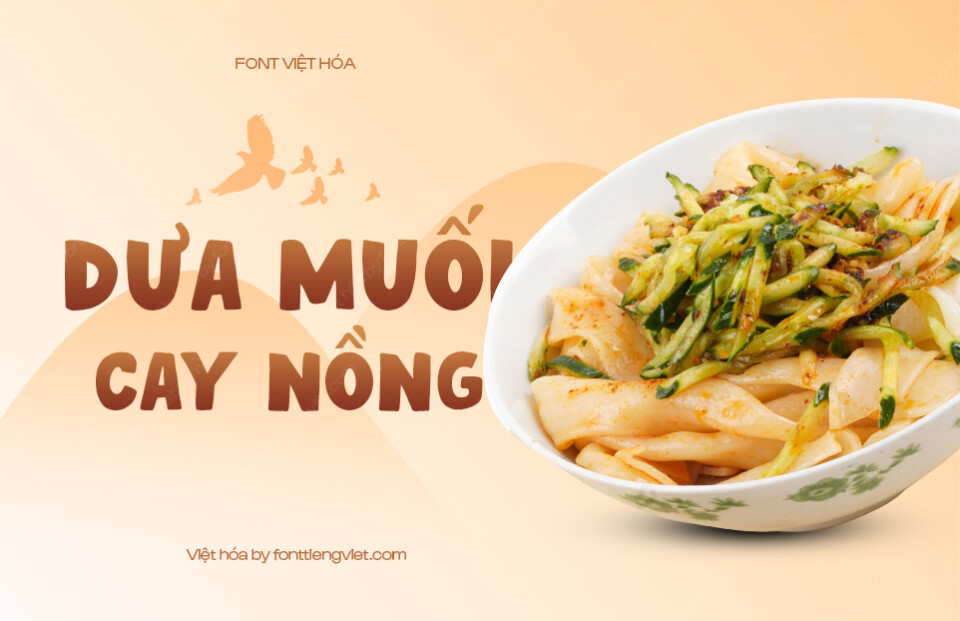
Giới thiệu về bộ Font Việt hóa 1FTV VIP Moro Baby
Trong thế giới đồ họa dành cho lứa tuổi mầm non và học sinh, việc lựa chọn một Font Chữ phù hợp là yếu tố tiên quyết để tạo nên sự gần gũi. Font Việt hóa 1FTV VIP Moro Baby xuất hiện như một giải pháp hoàn hảo, mang đến phong cách vui nhộn và hồn nhiên. Với các đường nét bo tròn mềm mại, bộ phông này giúp các bài giảng điện tử hay thiệp mời trở nên sinh động hơn bao giờ hết. Đây là lựa chọn lý tưởng cho thầy cô và phụ huynh muốn tạo ra những sản phẩm giáo dục mang tính thẩm mỹ cao.
Đặc điểm nổi bật của Font Việt hóa 1FTV VIP Moro Baby
Thiết kế ngộ nghĩnh và đầy sáng tạo
Điểm mạnh nhất của Font Việt hóa 1FTV VIP Moro Baby chính là cấu trúc chữ cái không đối xứng, tạo cảm giác như những nét vẽ tay của trẻ nhỏ. Các ký tự được chăm chút kỹ lưỡng để đảm bảo tính dễ đọc nhưng vẫn giữ được sự tinh nghịch. Điều này giúp các bé không cảm thấy khô khan khi tiếp xúc với mặt chữ trong quá trình học tập.
Khả năng hiển thị đa dụng trên nhiều nền tảng
Bộ font này đã được tối ưu hóa hoàn toàn cho tiếng Việt, không còn lỗi dấu hay mất nét khi gõ trên các phần mềm thiết kế chuyên nghiệp như Canva, Photoshop hay PowerPoint. Sự linh hoạt này giúp người dùng tiết kiệm thời gian chỉnh sửa, tập trung tối đa vào việc sáng tạo nội dung cho trẻ em.
Ứng dụng thực tế và cách cài đặt hiệu quả
Kết luận về bộ phông chữ Moro Baby